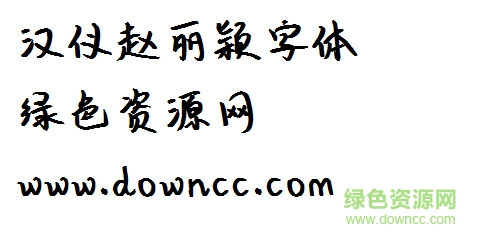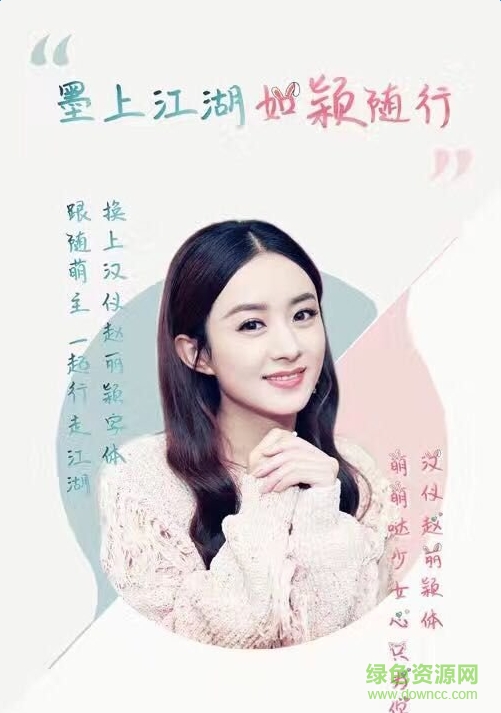
漢儀趙麗穎字體是一款漢儀類趙麗穎字體軟件,趙麗穎的字體給人非常舒服的感覺,深受廣大年輕人的喜愛,還有更多好看字體盡情期待,歡迎到綠色資源網(wǎng)下載體驗(yàn)!
趙麗穎的字曝光后,清秀、小巧的字體得到好評(píng)。就在近日,其字體被漢儀字庫(kù)收錄,且分為“少女心”和“江湖氣”兩版,以供粉絲下載使用。在趙麗穎以往詮釋的角色中,既有少女氣十足的宋暖、薛杉杉,也有江湖女俠范十足的碧瑤、花千骨等,角色與此次收錄的字體版本相得益彰。小編此次給大家?guī)淼氖菨h儀趙麗穎字體。